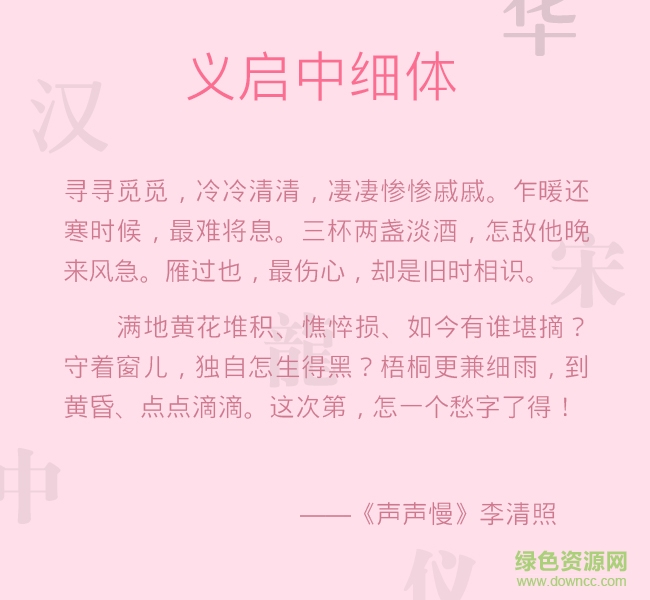
義啟中細體字體是一款義啟類耐看型字體軟件,中細體以簡約細膩的筆畫,給人非常有活力的感覺,整體效果工整有勁,非常耐看,感興趣的朋友歡迎來綠色資源網(wǎng)下載體驗!
義啟中細體是一款中文sans黑體。由于顯示硬件更新?lián)Q代,顯示像素增大,對字體的細節(jié)處要求極高。中細體在遵循傳統(tǒng)黑體的一般特點上加入更多新元素,筆畫與字形比例加大,字體重心在同一軸線上,增強了易讀性。義啟中細體,筆畫與字形比例小于1:20,筆畫更加纖細,在高分辨率顯示屏幕上顯示質(zhì)感非常好;結構重心在同一軸線上,整個字方正重心微上,生機勃勃;字間距隨著筆畫和字形比例變小也做了相應的調(diào)整,整體讀來字字珠璣又一脈相承。